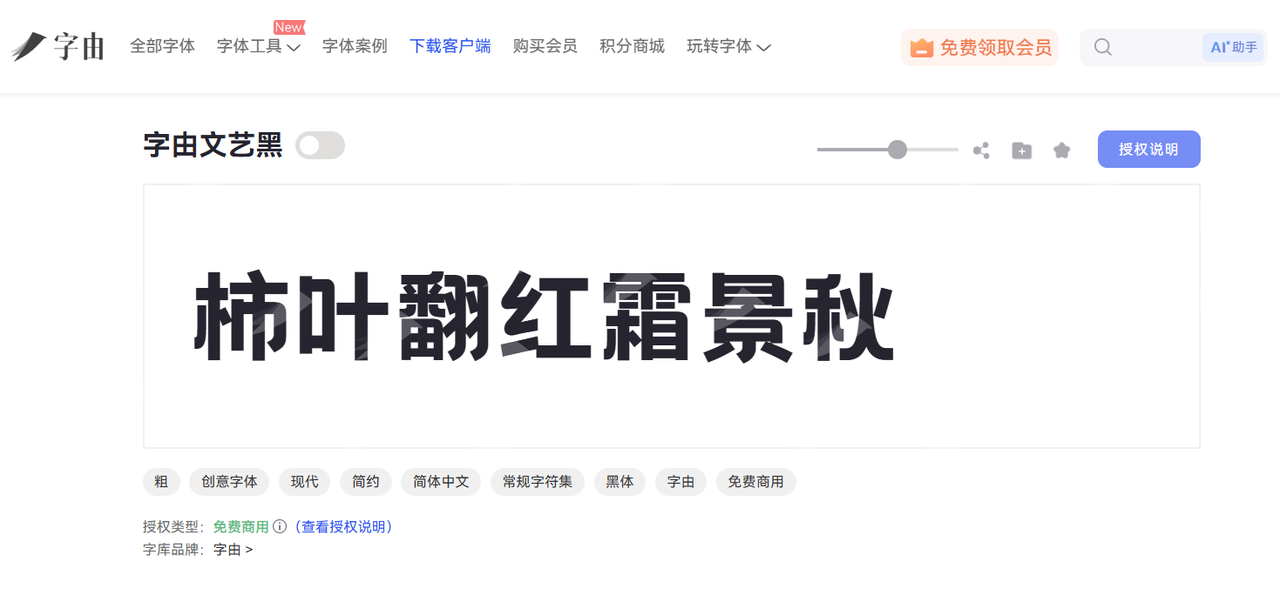
适合制作优惠券的字体整理!8款提升设计质感的字体推荐
在电商行业,优惠券设计不仅需要突出折扣信息,也需要兼顾品牌形象和用户的阅读体验。一款契合商品风格的字体能够帮助优惠券更好地传递活动主题,比如餐饮优惠券要体现轻松活泼的氛围,品牌会员券则更适合简洁大方的视觉风格。今天本文整理出 8 款适合制作优惠券的字体,考虑到还有做外贸设计的朋友,所以本文也提供了一些英文字体。接下来,一起来看看有没有适合你使用的字体素材吧!
一、中文优惠券字体推荐
1、字由文艺黑
字由文艺黑十分具有视觉设计感,在优惠券设计场景中,我们可以将它作为优惠券的标题,品牌的宣传语,优惠活动的名称来使用。
虽然具备设计感,但字由文艺黑并不会影响用户正常的阅读体验。它的字形比较规整,在突出折扣信息的同时,不会影响整体版面的平衡,比较适用于餐饮优惠券、电商促销券、会员福利券等多种场景,能够帮助设计保持简洁自然的视觉效果。
2、抖音美好体
抖音美好体在字由站内也有收录。它是一款具有年轻化特点的中文字体,整体风格轻松活泼,比较适合用于具有社交属性和活动氛围的优惠券设计。比如奶茶优惠券、美食套餐券、品牌活动券等场景,都可以利用这款字体来增强视觉吸引力。
而且抖音美好体的字形十分具有亲和力,也可以用作折扣活动标题、新品推广信息以及节日优惠文案使用。这款字体使用时,同样可以访问【字由】官网,使用字体名称来进行搜索查找。
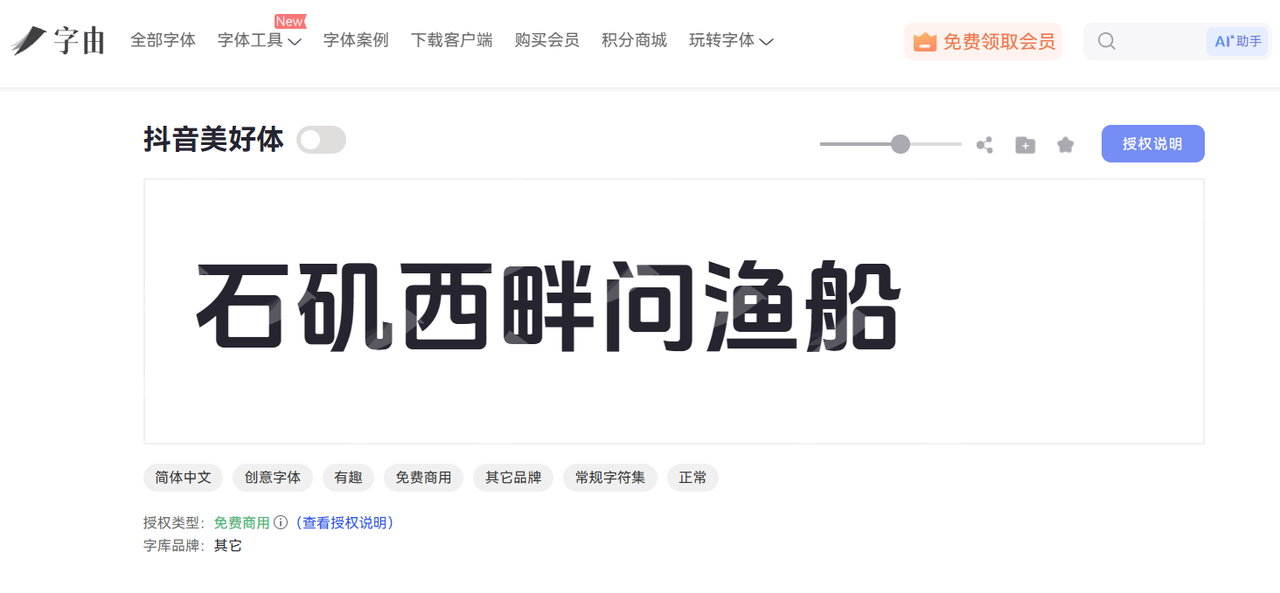
3、站酷快乐体
站酷快乐体的风格比较活泼,整体视觉感较为轻松,对于儿童品牌、餐饮活动、节日促销这类需要营造愉悦氛围的优惠券设计来说十分合适。
它能够让文字呈现更加生动的效果,在实际使用时,我们可以搭配明快的色彩和插画元素,让优惠券整体更加符合年轻消费者的视觉偏好。
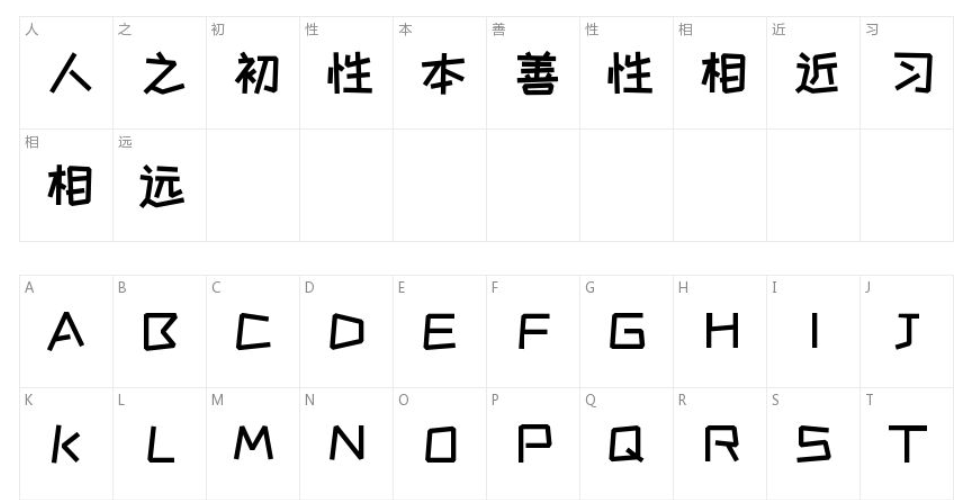
4、思源黑体
在优惠券中的信息展示部分,如果你比较阅读体验,那可以考虑一下思源黑体。它字体结构稳定,字形简洁,不管是用于价格信息、还是说明文字以及品牌介绍等位置都十分适合。当然,我们也可以用它来突出折扣信息,展示使用规则、有效时间、活动说明等内容。因此,正文区域更需要选择易读性较好的字体。
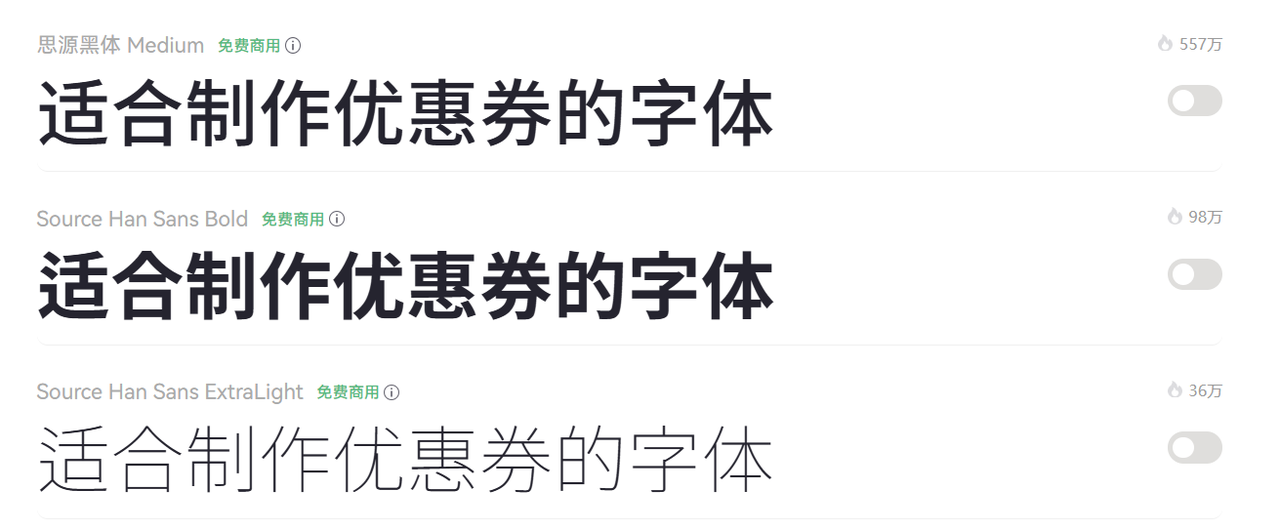
二、英文优惠券字体推荐
5、Montserrat
在英文优惠券的字体选择中,Montserrat 常用于现代商业设计。比如设计服装品牌优惠券、餐厅促销券以及线上活动页面时,我们可以用 Montserrat 来设计品牌名称、折扣信息或者活动主题。它字体结构简洁,字母比例协调,具有较强的识别性的同时也能够让重要信息更加突出,保持整体设计的现代感。
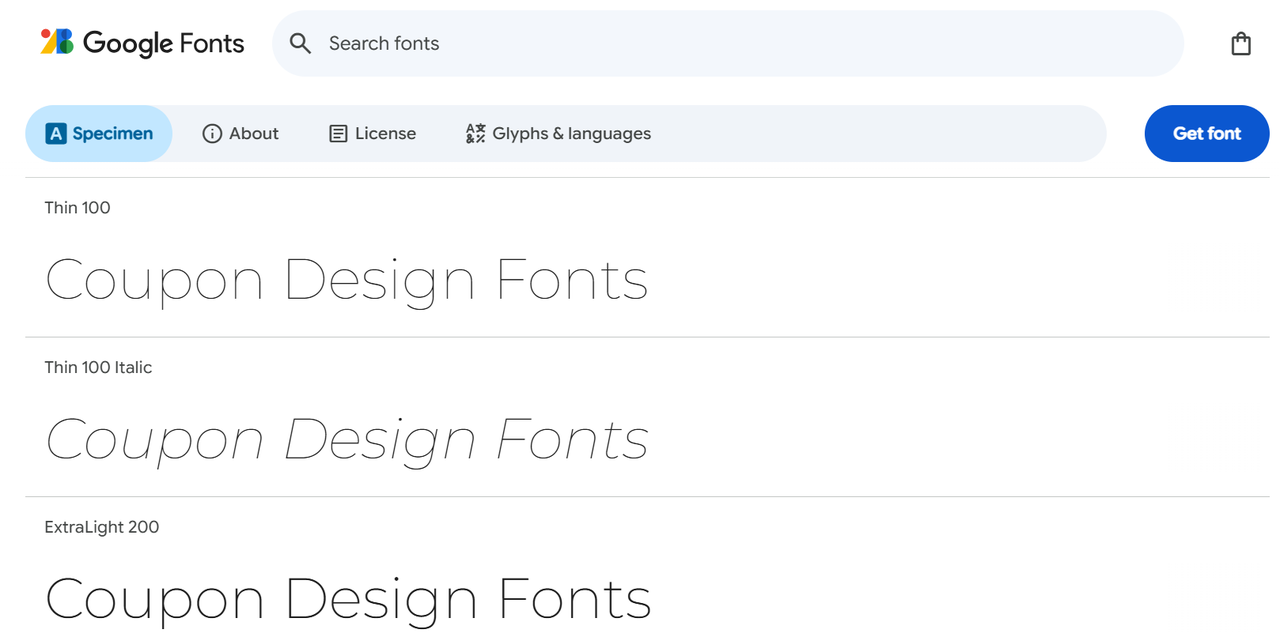
6、Playfair Display
Playfair Display 风格优雅,字母线条带有经典气质。当我们为高级餐饮、美妆品牌、精品零售等希望体验精致感的场景来设计优惠券时,就可以用 Playfair Display 来体现品牌特色,增强视觉效果。
有一点需要注意的是,Playfair Display 的装饰性较强,更适合作为短文本展示,不太建议用于大量说明内容。
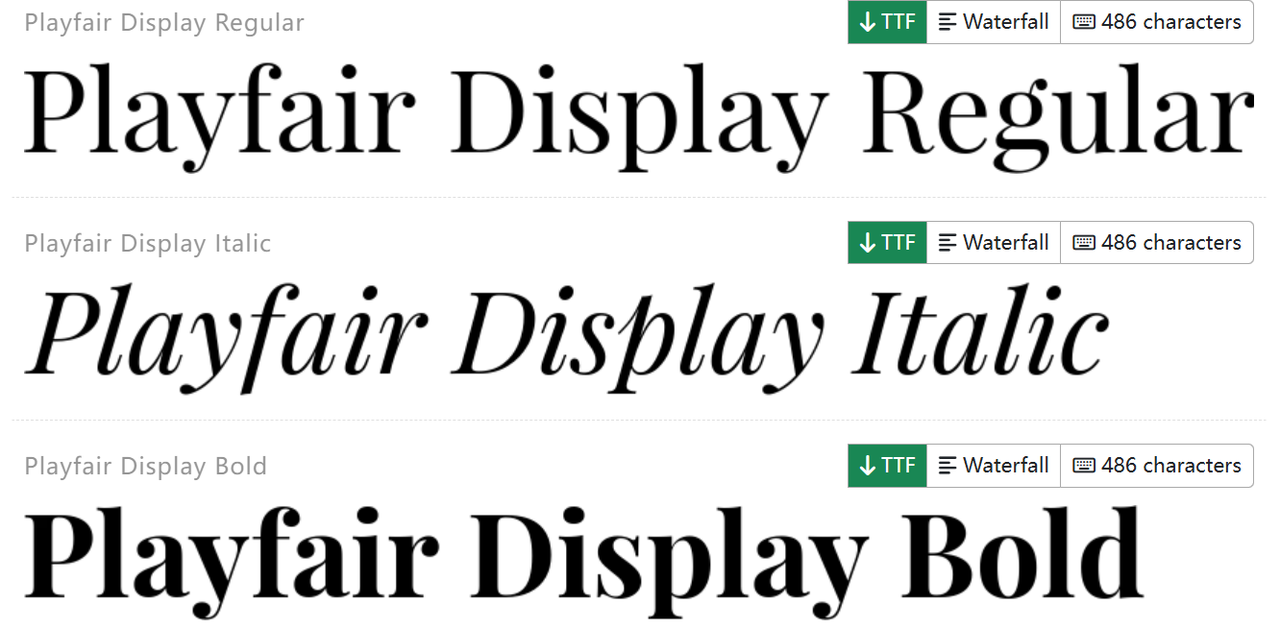
7、Bebas Neue
Bebas Neue 简洁有力,形态修长,可以在优惠券设计中突出数字和短标题,比如 "SALE" ,"OFF","SAVE" 这些优惠券设计中常见的英文信息,它能够帮助折扣信息形成明显视觉重点,吸引用户的注意力。如果你希望用户能一眼注意到优惠信息,我们可以将 Bebas Neue 的字号放大,并搭配简洁的背景。
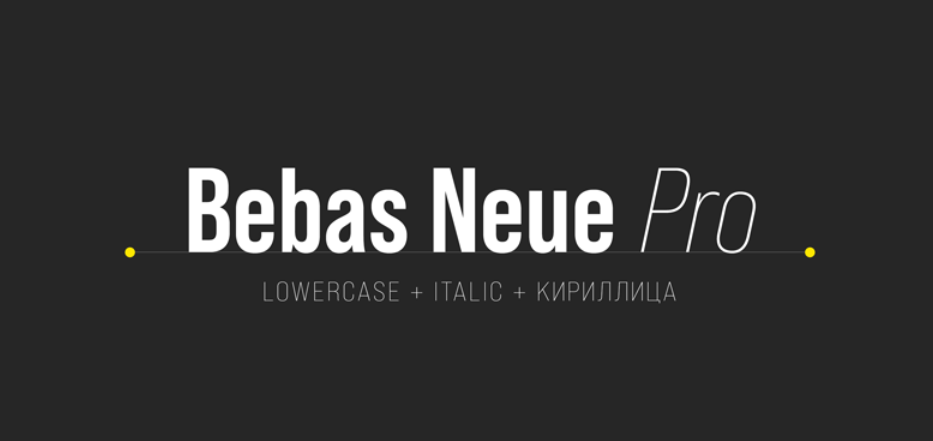
8、Poppins
对于年轻化品牌的优惠券设计,英文字体可以选择 Poppin。它是一款几何风格的字体,整体感觉清晰、视觉效果比较友好,可以应用于咖啡店、生活品牌、互联网活动等场景。
相比一些风格明显的字体,Poppins 具有较强的通用性,既可以用于标题,也可以用于辅助信息展示。如果优惠券整体设计偏简约风格,Poppins 还能够帮助页面保持统一和舒适的视觉体验。